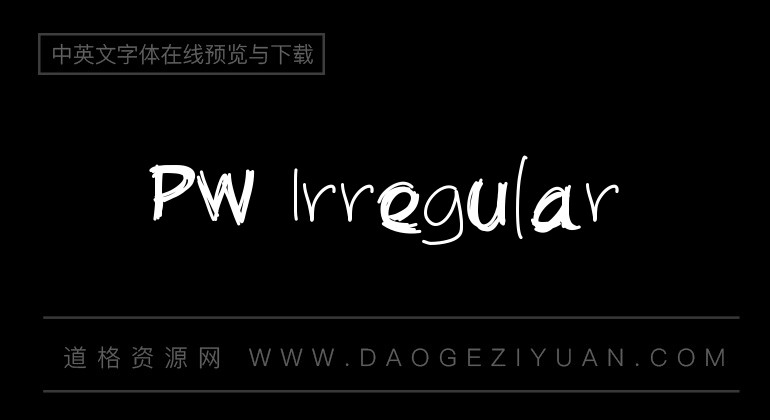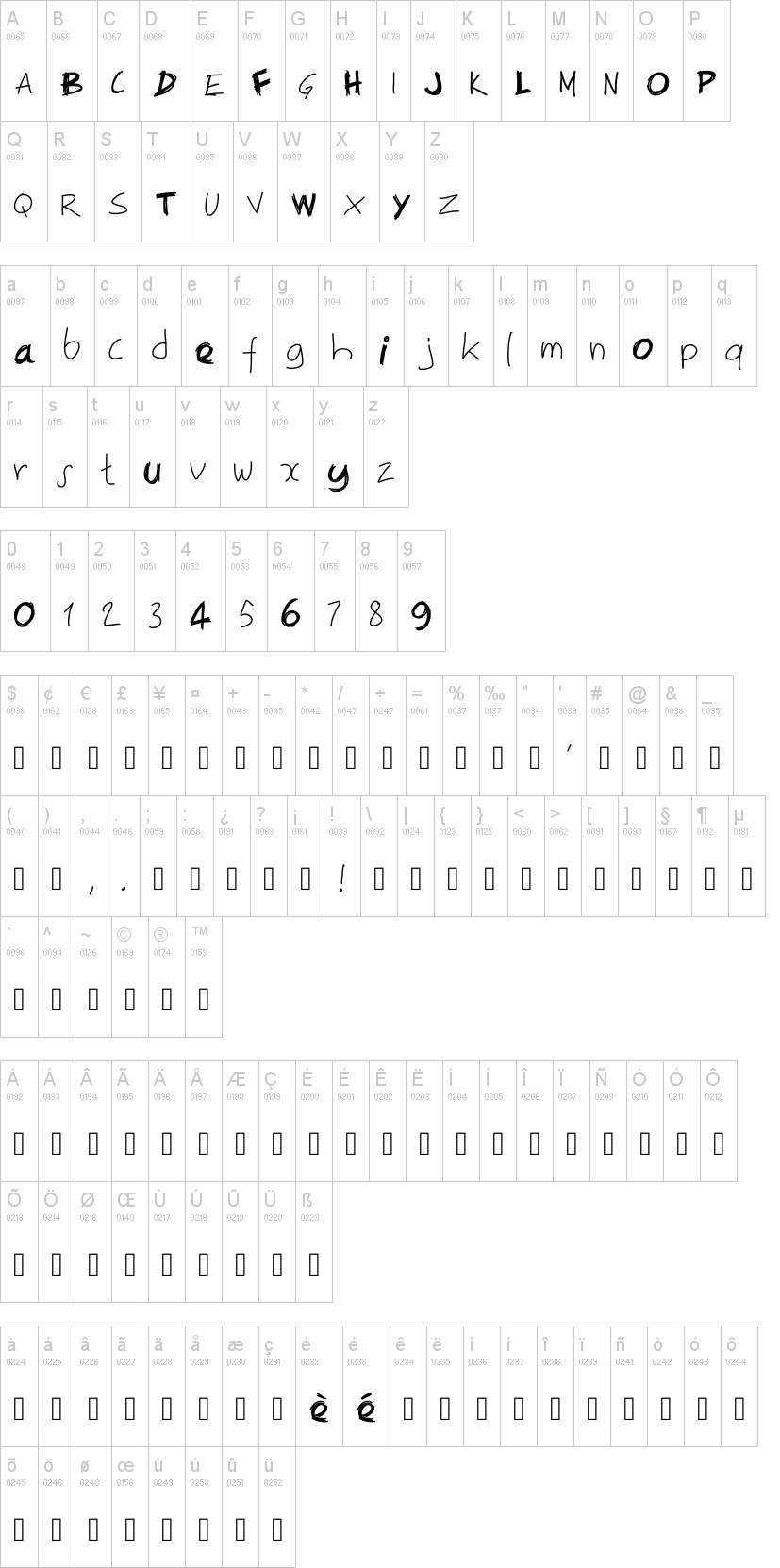
PW Irregular 是一款粗体字体,由英国设计师Paul Woods在2007年设计。它具有独特的粗糙和不规则的外观,有助于提升文本的可读性。这款字体可以用于印刷和网页设计,可以用于标题、标签和抬头,也可以用于设计logo。它的特点是字形粗糙,有趣的设计,可以让文本看起来更加有趣和有吸引力。内容介绍
PW Irregular是一款非常不错的手写艺术字体,具有很好的视觉感,适合于文化类的宣传设计、商业类品牌的广告和产品包装设计以及个性化文字排版等较多场景。